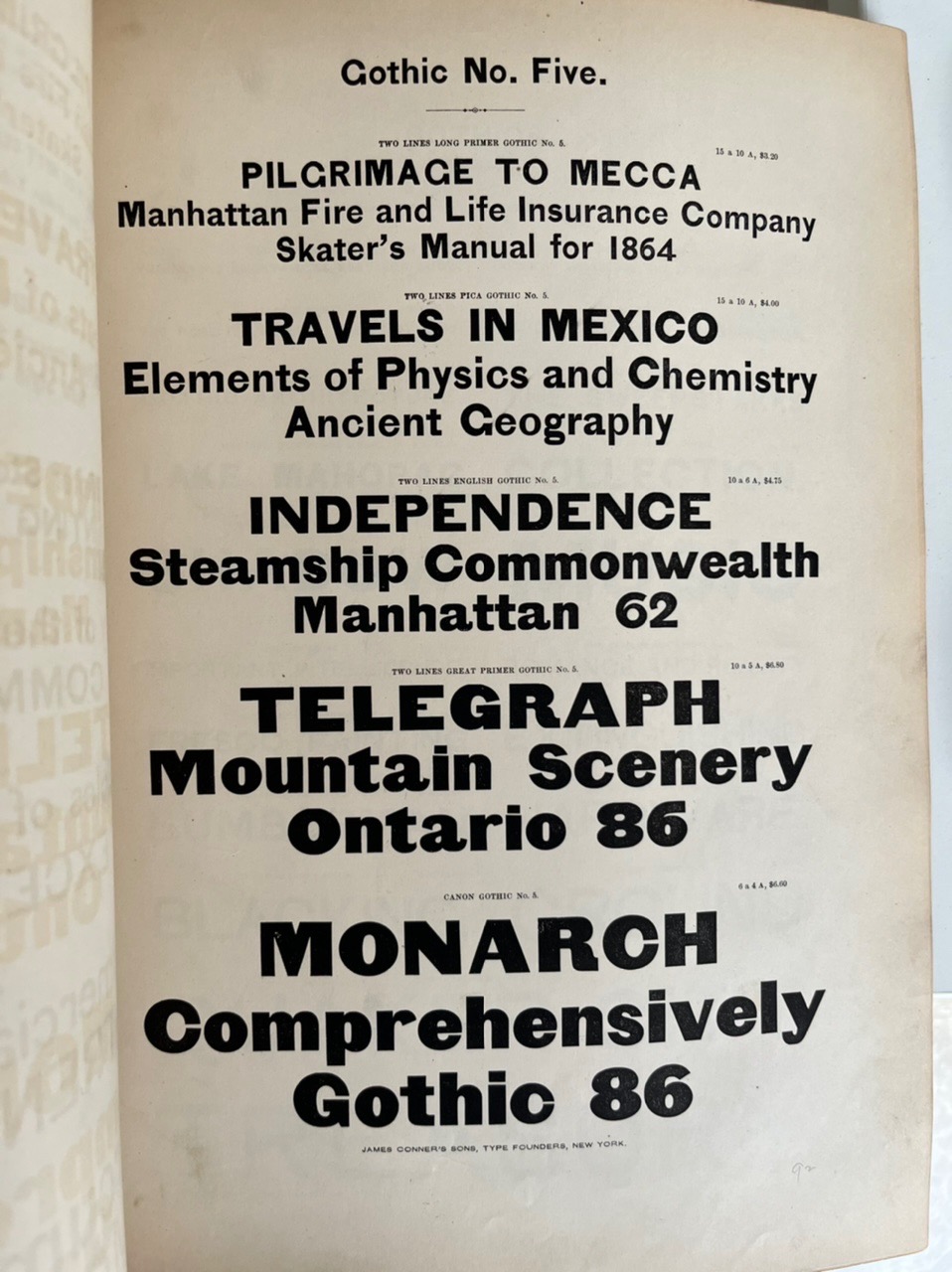
Was stört Dich hauptsächlich?
Beim Schmetterling sollten ab »metterling« alle Buchstaben  verbunden sein. Wenn »im« bei der Schrift geht, sollte »in« auch möglich sein.
Alle übrigen Schriftzüge sind schlecht bis sehr schlecht ausgeglichen.
Für »Pavillion« wäre eine Schrift dieser Art günstiger, wo die schrägen Buchstabenstämme deutlich steiler verlaufen - dann ließe sich das besser optisch ausgleichen.
Ob man die I-Punkte wie Notenköpfe gestalten sollte (diese sind ja nicht rund, sondern ovalsymetrisch) - ich weiß es nicht, das müsste man probieren. Auf jeden Fall machte ich die Punkt etwas kleiner und wies ihnen einen Grauwert zu - in schwarz stechen sie zu sehr hervor.
Ich finde das Schmetterlingsblatt eigentlich ganz charmant. Ist halt Lettering. Welcher Gebrauchsgrafiker der aktuellen Computer-Generation kann heute schon noch so ein komplettes Blatt frei zeichnen? Klar, mit Computerschriften können wir leicht die Zurichtung so lange optimieren, bis alles perfekt passt. Aber es ist fraglich, ob man diesen Maßstab für Lettering-Arbeiten ansetzen sollte.
Gothic No. 5    :biglove:
Die hat aber ein sehr offenes G. :-o
Die hat aber ein sehr offenes G.
Ich sehe ein sehr offenes (erste Zeile) und ein sehr geschlossenes G (letzte Zeile). Wenn man sich C & c in den unterschiedlichen Größen anschaut wird auch da sehr stark variiert ... :-P